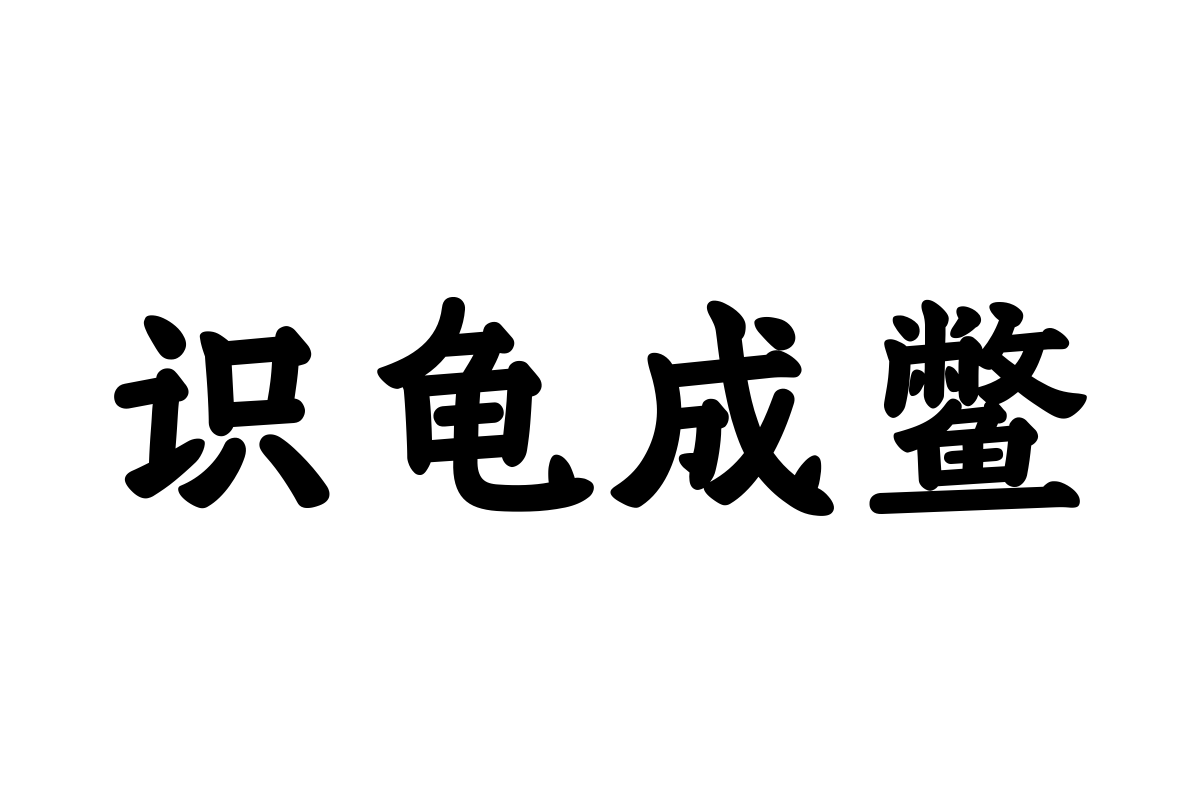
汉仪花冠-85 是一款由汉仪公司设计并发布的字体。这款字体以其独特的设计和优雅的外观而受到广泛欢迎。它适用于各种需要美观和专业设计的场合,如广告、海报、书籍、杂志等。
汉仪花冠-85 的特点在于其独特的字形设计和丰富的字重选择。这款字体采用了现代的设计手法,使得每个字都显得独特而又不失协调。它的笔画流畅,结构紧凑,给人一种清晰明了的感觉。此外,汉仪花冠-85 还提供了多种字重选择,以满足不同设计师的需求。
总的来说,汉仪花冠-85 是一款适合用于商业和设计领域的高质量中文字体。它不仅具有优美的外观,还提供了强大的功能和灵活性,可以满足各种设计需求。